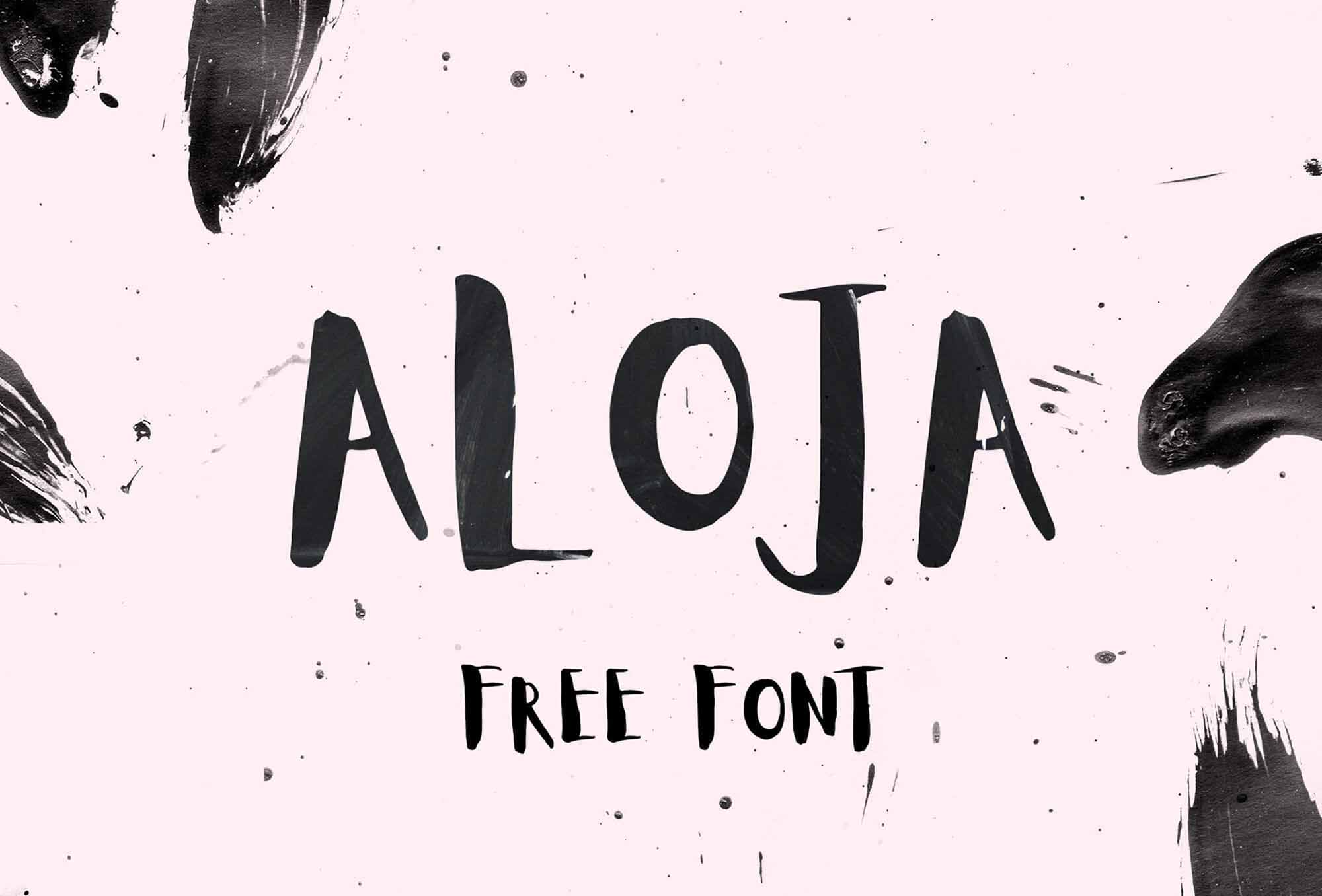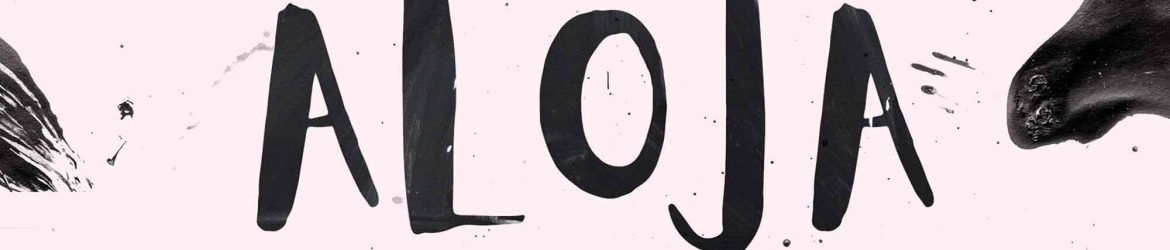
Aloja Handwritten Font – Download Grátis
Aloja é uma fonte de letra à mão livre criada pela dupla Ieva Mezule e Krisjanis Mezulis, em parceria com a WildOnes Design. Ela é perfeita para quem busca equilibrar beleza e utilidade em seus projetos de design. Essa fonte de letra à mão é uma ótima opção para aquelas criações que precisam ser legíveis, além de adicionar um toque de elegância e personalidade ao design. Como dizia alguém muito bem, a beleza do tipo reside em sua utilidade; apenas a beleza não legível serve a ninguém. Com Aloja, você pode criar designs que encantam os olhos e os ajudam a comunicar suas mensagens de forma eficaz. Este recurso gráfico é uma maneira de dar um toque único às suas criações, fazendo de cada projeto algo especial.